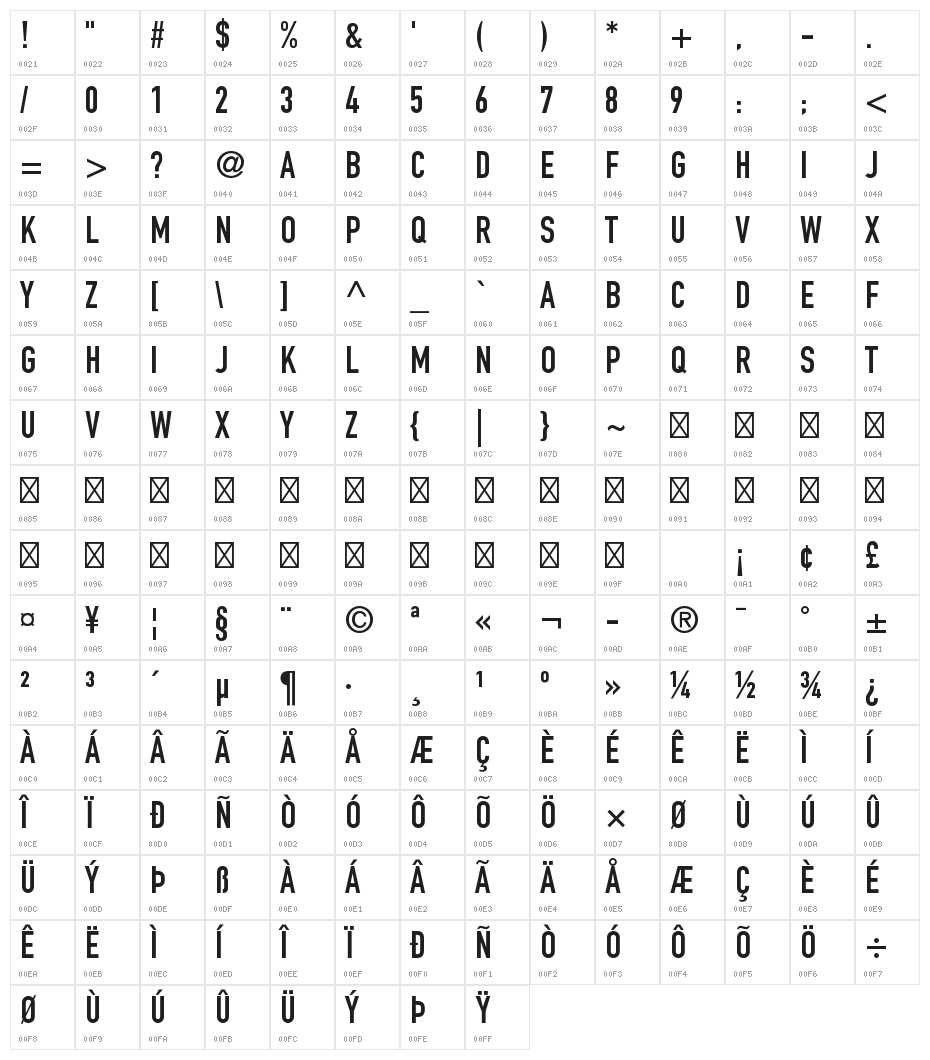
Engschrift Caps Font
| Anwendungsfall | Headlines, Logos, Signage |
| Vorgeschlagene Projekte | Ideal for use in signage, posters, and branding where bold, clear messaging is essential. Suitable for transportation graphics, packaging, and editorial headlines. |